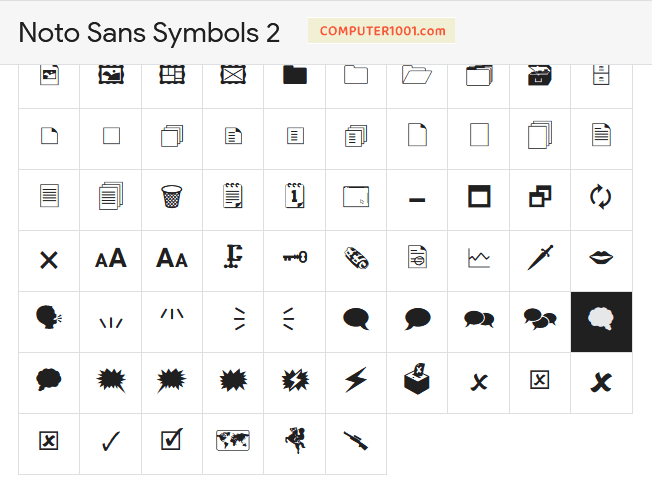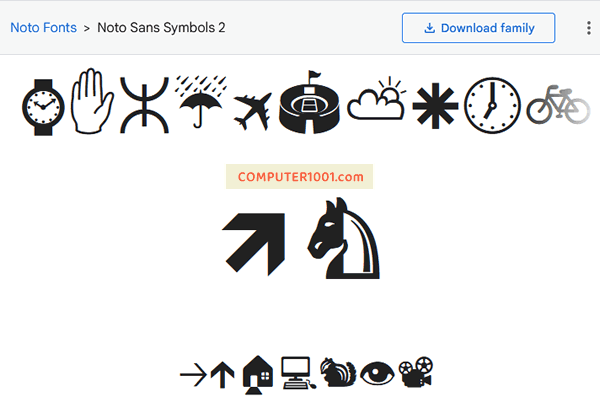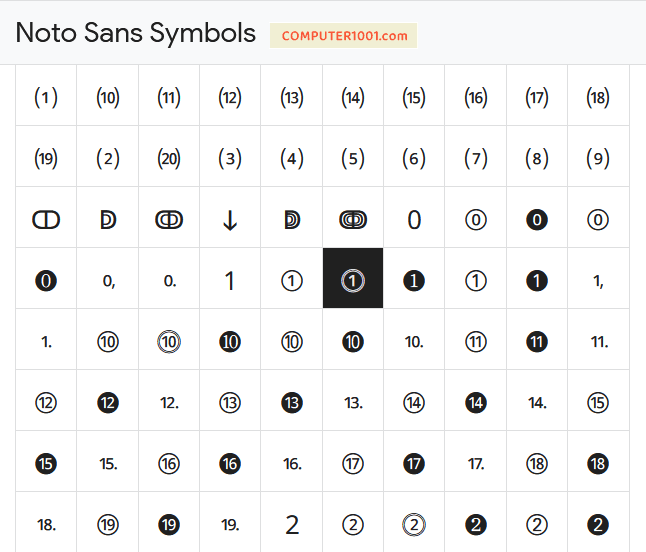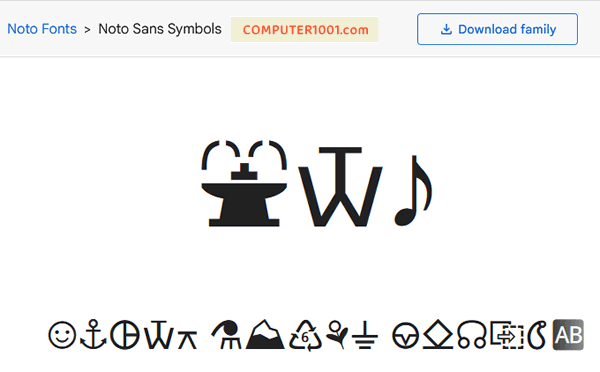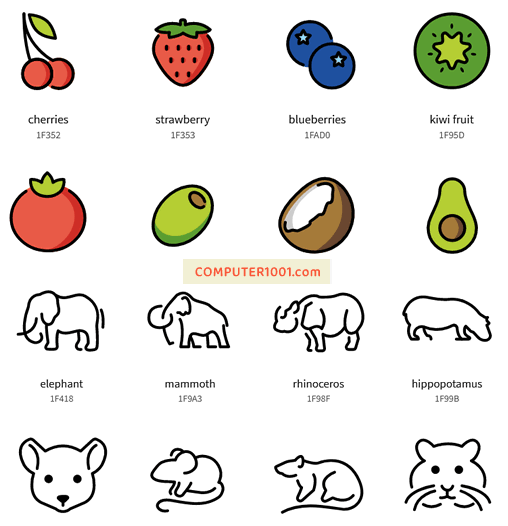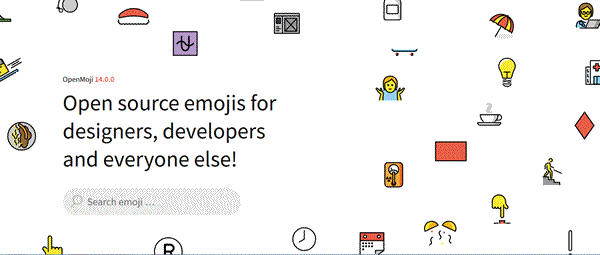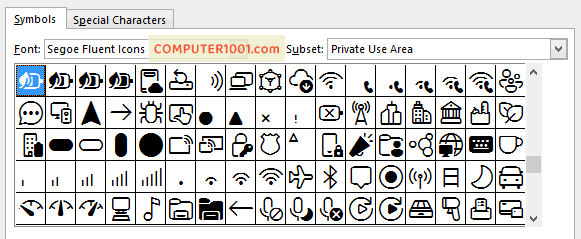
Di artikel ini, Anda bisa mendapatkan 6 set font emoji atau font icon gratis dengan total 15 ribu lebih simbol.
Font Noto Emoji
Noto Emoji adalah font yang dikembangkan oleh Google untuk memenuhi kebutuhan semua gambar emoji, termasuk spesifikasi emoji Unicode terbaru dengan total 3.663 emoji.
“Noto” dalam bahasa Latin berarti “saya menulis, saya tandai, saya perhatikan”.
Nama ini juga merupakan kependekan dari “no tofu” yang diartikan sebagai “tanpa tahu”, karena proyek ini bertujuan untuk menghilangkan ‘tahu’: yaitu kotak persegi panjang kosong yang ditampilkan ketika tidak ada font yang tersedia untuk teks Anda.
Emoji pada font ini memiliki desain yang sederhana dan detil yang lebih sedikit dibandingkan dengan emoji biasa.
Koleksi simbol dari font Noto Emoji dibagi dalam kategori berikut:
• Smileys and emotions.
• Animal and nature (berbagai emoji hewan termasuk dinosaurus, naga, bunga, pohon, dan simbol cuaca)
• Travel and places.
• Activities and events (berbagai kegiatan olahraga, hobi, dan perayaan).
• Objects (seperti pakaian, tas, sepatu, telepon, buku, alat pertukangan, jam, kunci dan gembok).
• Symbols (aneka simbol hati, horoskop, tanda panah, dan lain-lain).
• Flags (berbagai bendera dengan inisial nama negara).
Contoh-contoh simbol bisa dilihat pada gambar berikut.
Gambar ikon bunga, buah, sayur, dan makanan
Font Noto Emoji Ikon Hewan dan Serangga
Gambar ikon hewan dan serangga
Font Noto Color Emoji
Font ini memiliki tampilan yang cantik karena warna emojinya yang berwarna-warni seperti font Segoe UI Emoji.
Font Noto Sans Symbols
Noto Sans Symbols mirip dengan koleksi simbol pada font Arial Unicode MS. Akan tetapi font ini memiliki lebih banyak variasi simbol dengan total 1.224 dan masih ada kelanjutannya pada versi 2 di bawah ini.
Font ini memiliki:
• Simbol angka dalam lingkaran, tanda kurung, dan angka romawi.
• Simbol huruf besar dan kecil dalam tanda kurung dan kotak.
• Simbol alkimia.
• Dan simbol lain seperti lambang farmasi atau logo apotek berupa gambar cawan dan ular serta logo kedokteran yang disebut staff of aesculapius.
Font Noto Sans Symbols Angka Dalam Lingkaran
Font Noto Sans Symbols 2
Font Noto Sans Symbols 2 memiliki 2.674 simbol.
Antara lain:
• Numbers, yaitu angka dalam berbagai bahasa atau kode. Juga memiliki angka digital 0 – 9.
• Arrows, berbagai bentuk tanda panah.
• Geometric Shapes, berbagai bentuk geometris.
Serta berbagai dingbats seperti pada font Wingdings, namun dengan variasi obyek yang lebih banyak. Seperti icon gunung, tenda, stadium dan bendera, speaker, surat (icon email), dokumen, serta gelembung bicara (speech bubble) atau ikon chatting.
Contoh Font Noto Sans Symbols 2
Font OpenMoji
Font OpenMoji adalah font emoji gratis dengan lisensi Creative Commons (Attribution-ShareAlike 4.0 International).
Font ini merupakan proyek open source dengan total 4.083 emoji yang memiliki berbagai simbol bendera, orang, hewan dan tumbuhan, makanan dan minuman, aktivitas, serta bangunan dan alat transportasi.
Contoh Font OpenMoji
OpenMoji juga tersedia dalam bentuk gambar SVG dan PNG (hitam dan berwarna). Untuk setiap simbol orang memiliki 4 variasi warna kulit atau warna rambut.
Keterangan font:
• Format Black.ttf untuk digunakan di aplikasi seperti Micrsoft Word, Excel, dan PowerPoint.
• Sedangkan Color.ttf untuk digunakan di aplikasi Adobe, web browser, dan lain-lain.
Font Segoe Fluent Icons
Segoe Fluent Icons merupakan font bawaan pada Windows 11. Namun Microsoft memberikan download untuk pengguna Mac dan Windows versi sebelumnya.
Font ini diperkirakan memiliki sekitar 4.000 simbol.
Bentuk font Segoe Fluent Icons sangat jauh berbeda dengan Segoe UI Symbols, karena font ini awalnya dirancang untuk aplikasi seluler.
Oleh sebab itu, font Segoe Fluent Icons memiliki banyak simbol baterai, gambar sinyal hp, wifi, tanda panah, kaca pembesar, dan simbol hati.